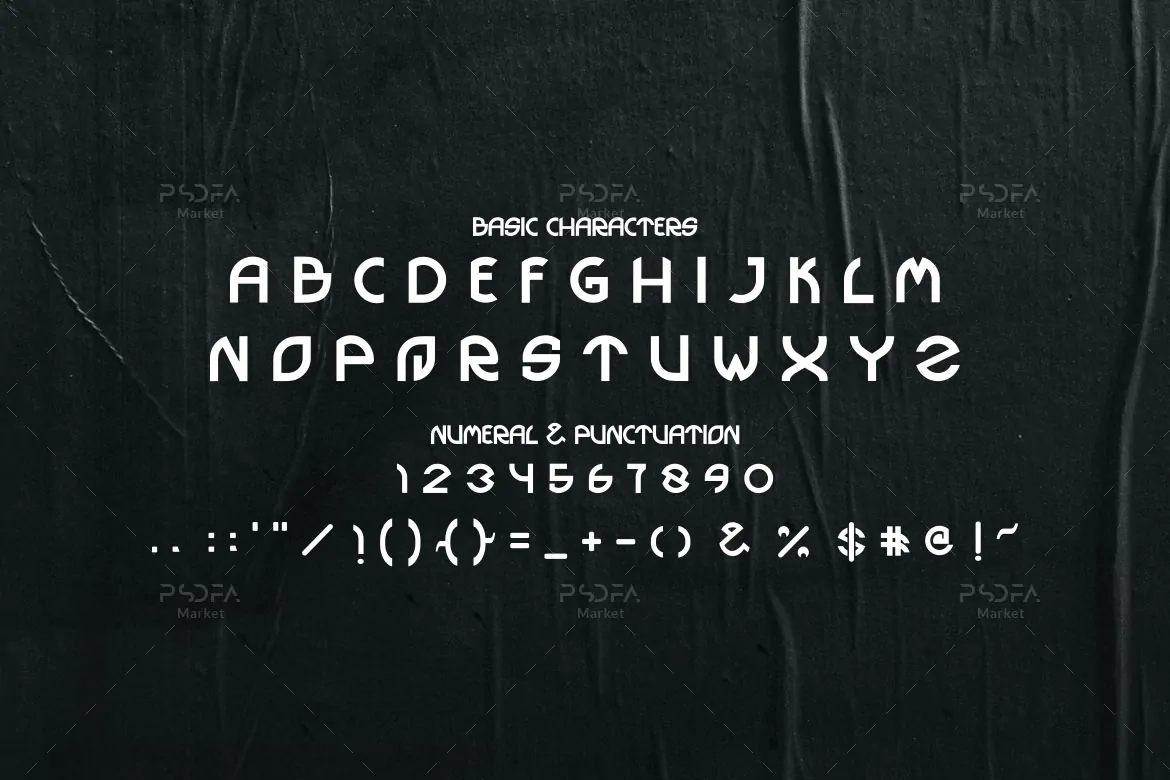
فونت انگلیسی مدرن و زیبای Oxarky
فونت انگلیسی مدرن و زیبای Oxarky یک قلم سنس سریف است که مناسب جهت استفاده در طرحهای گرافیکی مختلف به خصوص طراحی لوگو میباشد. فونت Oxarky با وزن معمولی طراحی شده است که میتوانید از آن در طراحی انواع کارت ویزیت، بروشور، تراکت، پوستر، لوگو، بسته بندی محصولات و … استفاده کنید.